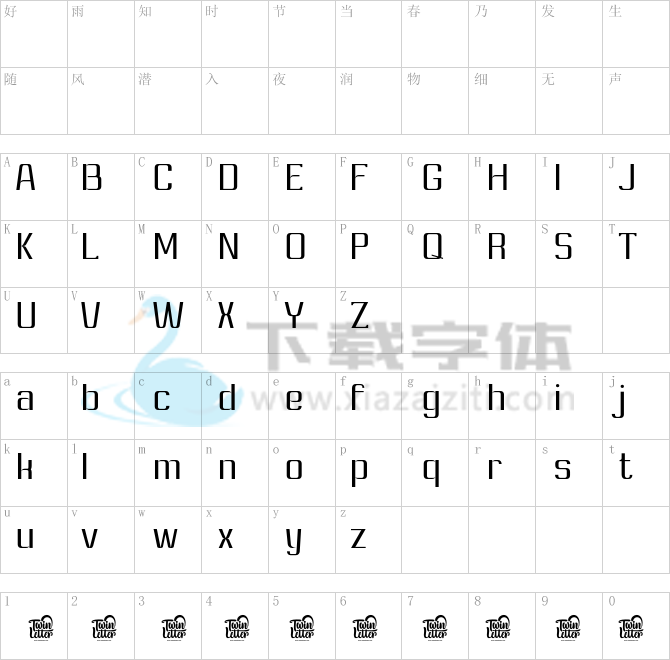
Ashety Light.otf字体下载,这款字体结构工整、笔画清晰,兼顾美观与易读性,适用于标题、正文、海报、包装、LOGO 等多种场景。字形优雅稳定,风格百搭耐看,适配日常排版与创意设计,让文字呈现更舒适、更具质感。Ashety Light.otf字体下载一笔一画,皆是细节,以均衡的比例、流畅的线条打造舒适视觉体验,字形端正大气,风格简约现代。无论是商业设计、品牌宣传还是日常排版,都能轻松驾驭,让文字更有格调与力量。Ashety Light.otf字体下载字体下载。
• 字体名称:Ashety Light